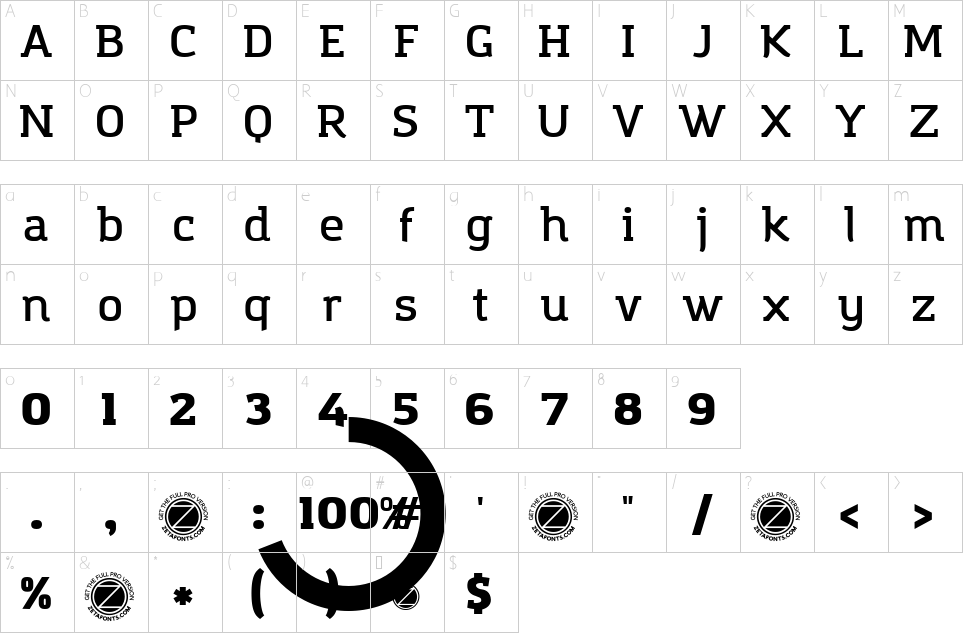
Descubra a fonte Amazing Infographic para criar infográficos incríveis em seu Windows ou Mac. Esta fonte foi criada pela Zetafonts e já foi baixada mais de 15.525 vezes. Ela é perfeita para criar infográficos profissionais e atrativos. Com Amazing Infographic, você pode destacar suas ideias de maneira criativa e informativa, tornando sua comunicação visual mais impactante. Baixe a fonte e transforme seus projetos de infográficos em verdadeiros cartões postais de estilo. Não perca mais tempo buscando fontes para seus projetos de infográficos. Amazing Infographic está aqui para ajudar.